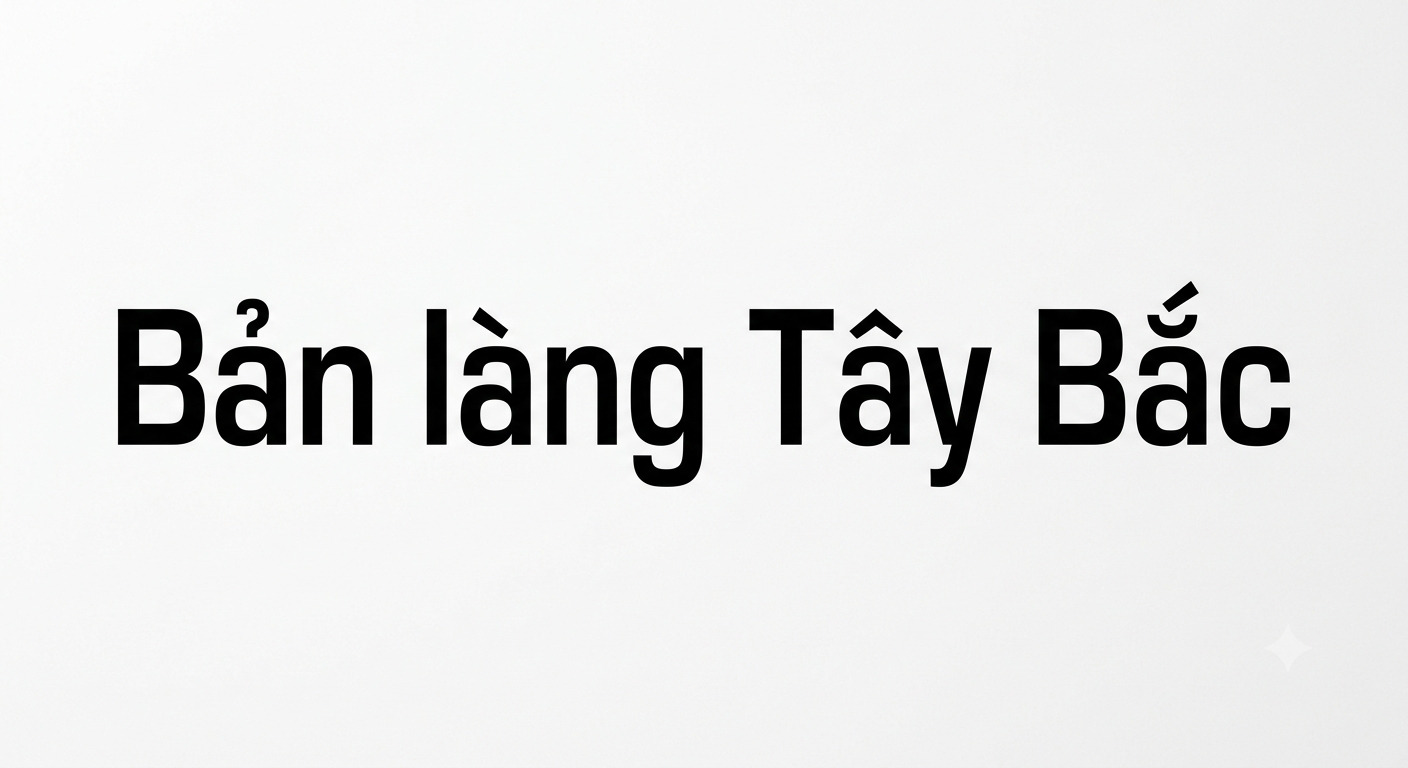
Nhiều designer khi sử dụng font Eurostile trong thiết kế nhận diện thương hiệu thường gặp lỗi thiếu dấu tiếng Việt hoặc đường nét bị vỡ khi phóng lớn để in ấn. Những lỗi hiển thị này có thể làm giảm tính đồng nhất của thiết kế, khiến bao bì và quà tặng doanh nghiệp thiếu sự chuyên nghiệp trong mắt khách hàng, đối tác.
Font Eurostile là gì?
Font Eurostile là một trong những phông chữ Sans-serif kinh điển được thiết kế bởi Aldo Novarese vào năm 1962. Được phát triển từ phông chữ Microgramma trước đó, Eurostile gây ấn tượng mạnh mẽ nhờ cấu trúc hình học vuông vức với các góc bo tròn tinh tế. Sự kết hợp giữa tính kỹ thuật dứt khoát và nét thẩm mỹ hiện đại đã giúp bộ font này trở thành biểu tượng của các ngành công nghiệp nặng, khoa học viễn tưởng và công nghệ cao trong suốt nhiều thập kỷ.
Đặc trưng nổi bật của Eurostile chính là các biến thể mở rộng, đặc biệt là Font chữ eurostile bold extended. Kiểu chữ này có chiều ngang rộng, tạo cảm giác vững chãi, uy lực dễ nhận diện ngay cả khi nhìn từ xa. Đây là lý do Eurostile thường xuyên xuất hiện trên logo của các hãng xe hơi danh tiếng, thiết bị điện tử và các biển chỉ dẫn tại các khu công nghiệp hiện đại. Bản việt hóa chuẩn tại Xưởng In Viva đã được xử lý dấu thanh tỉ mỉ, giúp các nhà thiết kế Việt Nam dễ dàng ứng dụng vào các dự án truyền thông mà không lo bị lỗi hiển thị.
Bảng kí từ font Eurostile
Lưu ý: Eurostile có cấu trúc chữ khá rộng theo chiều ngang. Khi dàn trang tiêu đề trên các bề mặt hẹp như bút ký hay tem nhãn sản phẩm nhỏ, bạn nên cân nhắc kỹ tỉ lệ để nội dung không bị tràn ra ngoài vùng an toàn.
5 ứng dụng của font Eurostile trong thiết kế và in ấn quà tặng
Vẻ đẹp hiện đại và đậm chất công nghệ của Eurostile giúp các sản phẩm bao bì, quà tặng doanh nghiệp trở nên chuyên nghiệp hơn khi kết hợp cùng các kỹ thuật in ấn và gia công phù hợp:
• Thiết kế bao bì thiết bị điện tử và sản phẩm công nghệ: Eurostile phù hợp để thể hiện tên thương hiệu, mã sản phẩm hoặc thông tin kỹ thuật trên hộp cứng đựng sạc dự phòng, tai nghe, đồng hồ thông minh. Cấu trúc chữ vuông vức tạo cảm giác chính xác, phù hợp với các sản phẩm mang phong cách hiện đại.
• Sản xuất set quà tặng văn phòng in logo: Sử dụng Font chữ Eurostile Bold Extended để in UV trên bình giữ nhiệt kim loại, sổ tay da hoặc sạc dự phòng giúp tạo điểm nhấn mạnh mẽ, phù hợp với các bộ quà tặng dành cho doanh nghiệp công nghệ, kỹ thuật.
• In ấn túi giấy thương hiệu cơ khí và ô tô: Eurostile có thể ứng dụng trên túi giấy Ivory, Kraft để thể hiện logo, slogan hoặc thông tin doanh nghiệp. Kiểu chữ gọn gàng giúp bộ nhận diện thương hiệu giữ được sự đồng bộ và chuyên nghiệp.
• Trang trí bảng biển và không gian showroom: Với định dạng vector, font Eurostile có thể sử dụng cho các tiêu đề lớn trên bảng hiệu, backdrop hoặc khu vực trưng bày sản phẩm, giúp duy trì độ sắc nét khi mở rộng kích thước thiết kế.
• Sản xuất kỷ niệm chương và vật phẩm vinh danh: Eurostile Bold phù hợp để khắc hoặc in tên doanh nghiệp, cá nhân lên pha lê, kim loại hoặc các vật phẩm lưu niệm, tạo cảm giác chắc chắn và trang trọng cho món quà.
Font Eurostile đẹp 01
Để font Eurostile hiển thị rõ nét khi đưa vào sản xuất thực tế, designer cần chú ý các yếu tố kỹ thuật sau:
• Điều chỉnh khoảng cách ký tự (Tracking): Eurostile, đặc biệt ở các biến thể Extended, có phần thân chữ rộng. Khi sử dụng trên bề mặt cong như bình giữ nhiệt hoặc ly sứ, nên cân chỉnh khoảng cách giữa các ký tự để bố cục không bị rời rạc.
• Tối ưu đường Path cho gia công bế nổi: Khi sử dụng Eurostile làm logo trên hộp quà cao cấp, file vector cần được xử lý các điểm góc vuông và đường viền chữ. Việc tối ưu path giúp khuôn dập nổi tái hiện rõ hình dáng chữ, hạn chế ảnh hưởng đến bề mặt giấy trong quá trình gia công.
• Kiểm soát độ dày nét chữ theo chất liệu in: Eurostile có nhiều biến thể từ Light đến Bold. Với các chất liệu có độ hút mực như giấy Kraft hoặc giấy mỹ thuật, nên ưu tiên Medium hoặc Bold để hạn chế tình trạng nét chữ bị nhạt sau khi in.